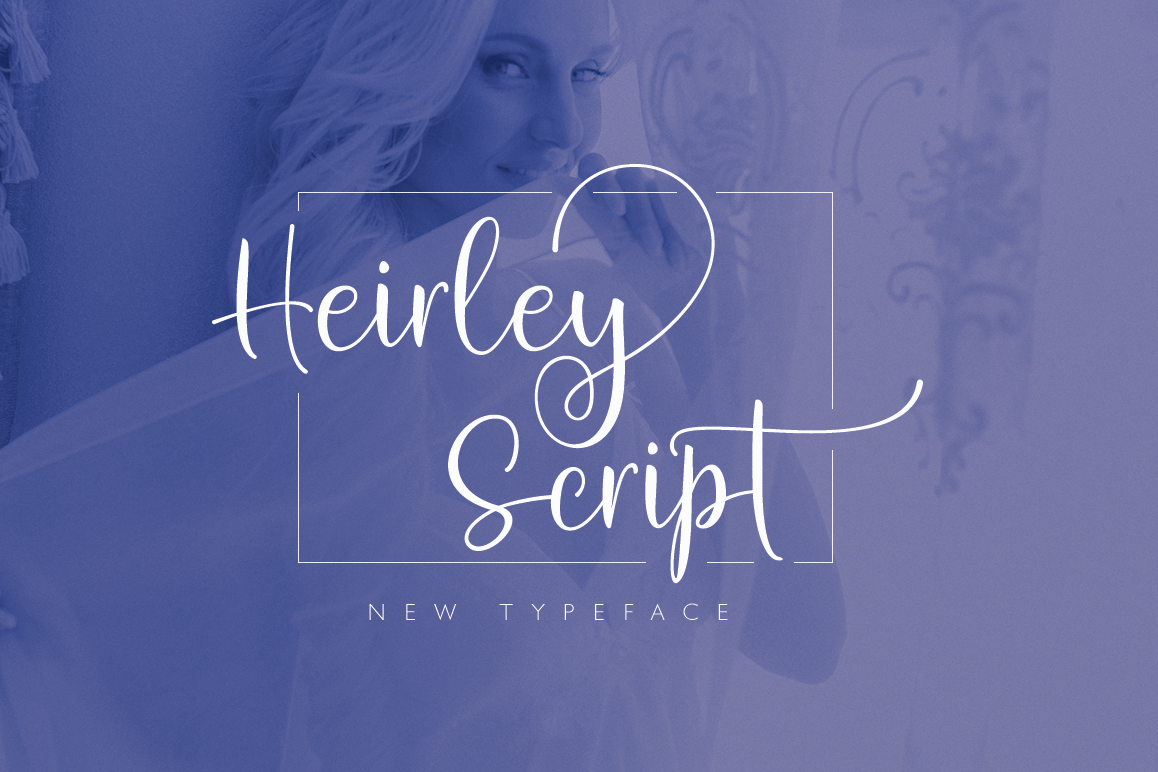
Heirley Script , itu adalah sikat font halus yang memiliki gaya yang berbeda. Ini adalah pilihan yang sempurna untuk proyek branding pribadi. Dapat digunakan untuk berbagai keperluan. Seperti pos, logo, undangan pernikahan, t-shirt, kop surat, label, berita, poster, lencana, dll. Untuk mengaktifkan pergantian OpenType Stylistic, Anda memerlukan program yang mendukung fitur OpenType seperti Adobe Illustrator CS, Adobe Indesign dan CorelDraw X6-X7. Fitur font ini adalah;
- Ikatan standar
- Alternatif Gaya
- Set gaya
- PUA Unicode (Area Penggunaan Pribadi)